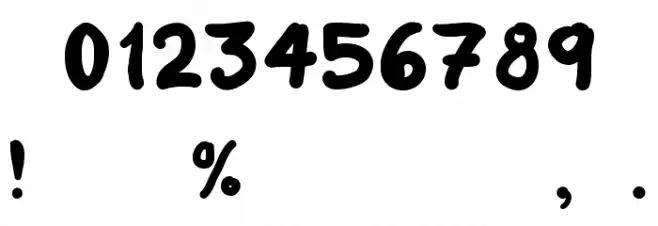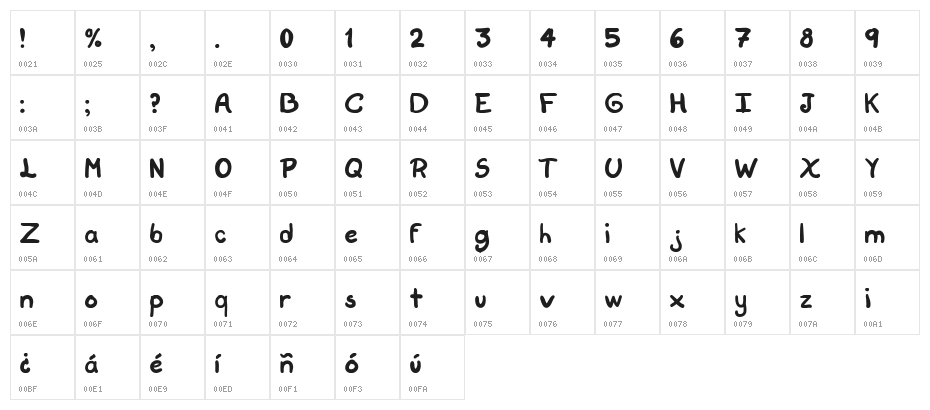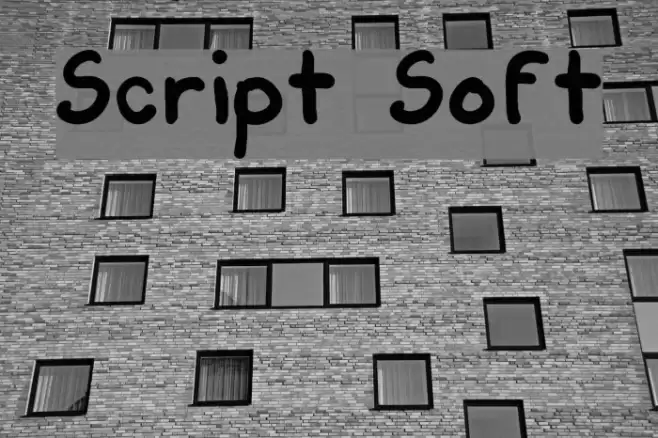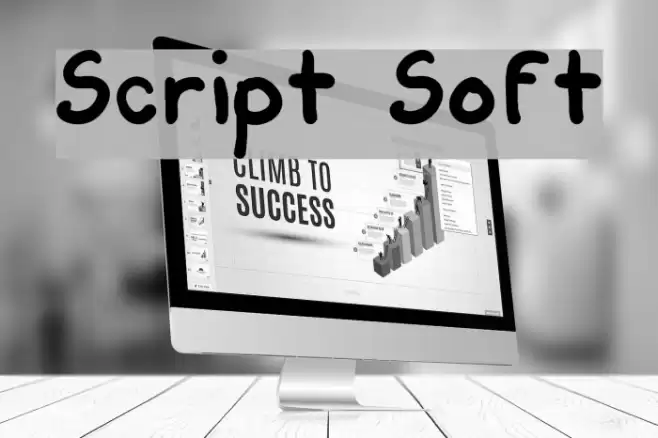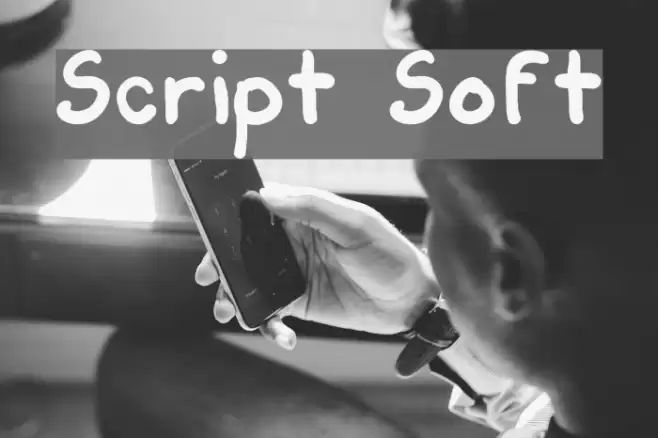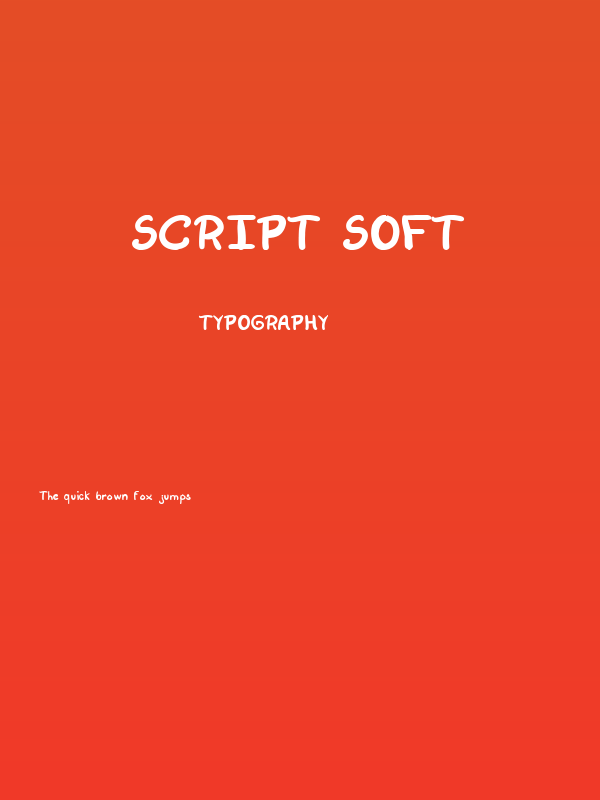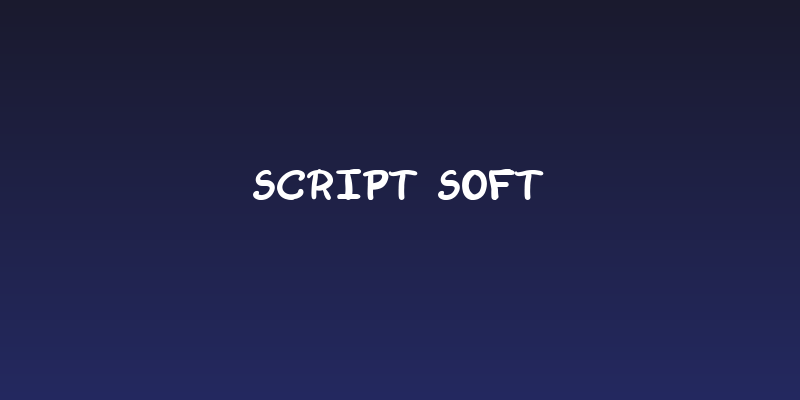
Script Soft Font
| Estilo general | Casual |
| Caso de uso | Headlines, Logos, Informal Text |
| Proyectos propuestos | Ideal for children's books, greeting cards, playful branding, and casual invitations. |